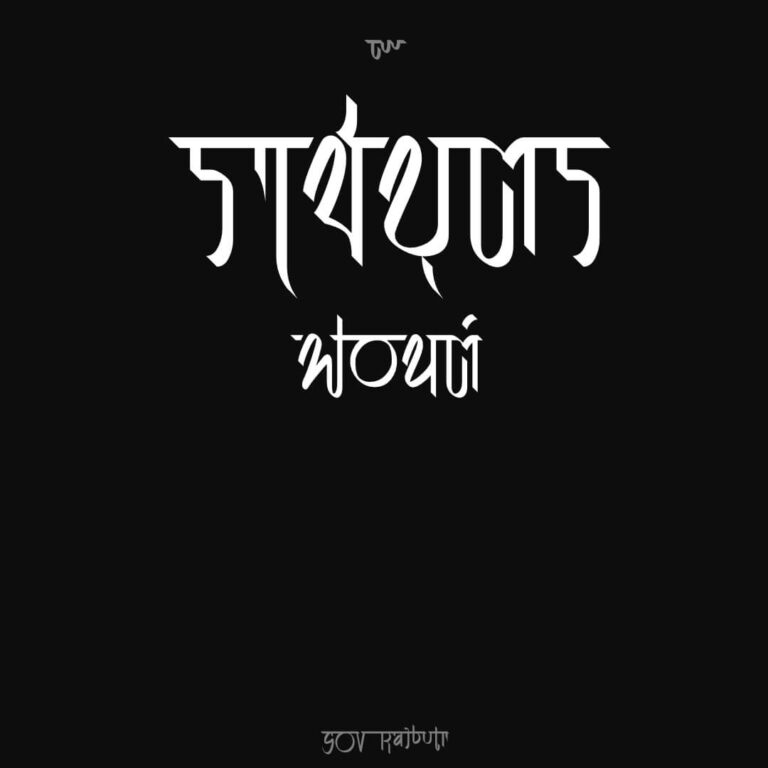
ซ่อนตัว (SOV_SornTua)
ฟอนต์ซ่อนตัว ออกแบบอักษรไทย ให้เป็น cursive font ถ้าเป็นการเขียนคือ ลากเส้นจนจบคำ จบประโยค แล้วค่อยมาเติมเส้นขวางเพื่อให้เป็นตัวอักษร แต่พอทำเป็นฟอนต์จะไม่สามารถเห็นสิ่งนี้ กลายเป็นเส้นที่ซ่อนอยู่
พิมพ์วงเล็บ 4 แบบ เพื่อเพิ่มเส้นยาวหน้าหลังให้คำโดดเด่น เส้นที่ซ่อนอยู่ รู้ได้โดยกด เอียง
เบื้องหลังการออกแบบ : ฟอนต์ ซ่อนตัว